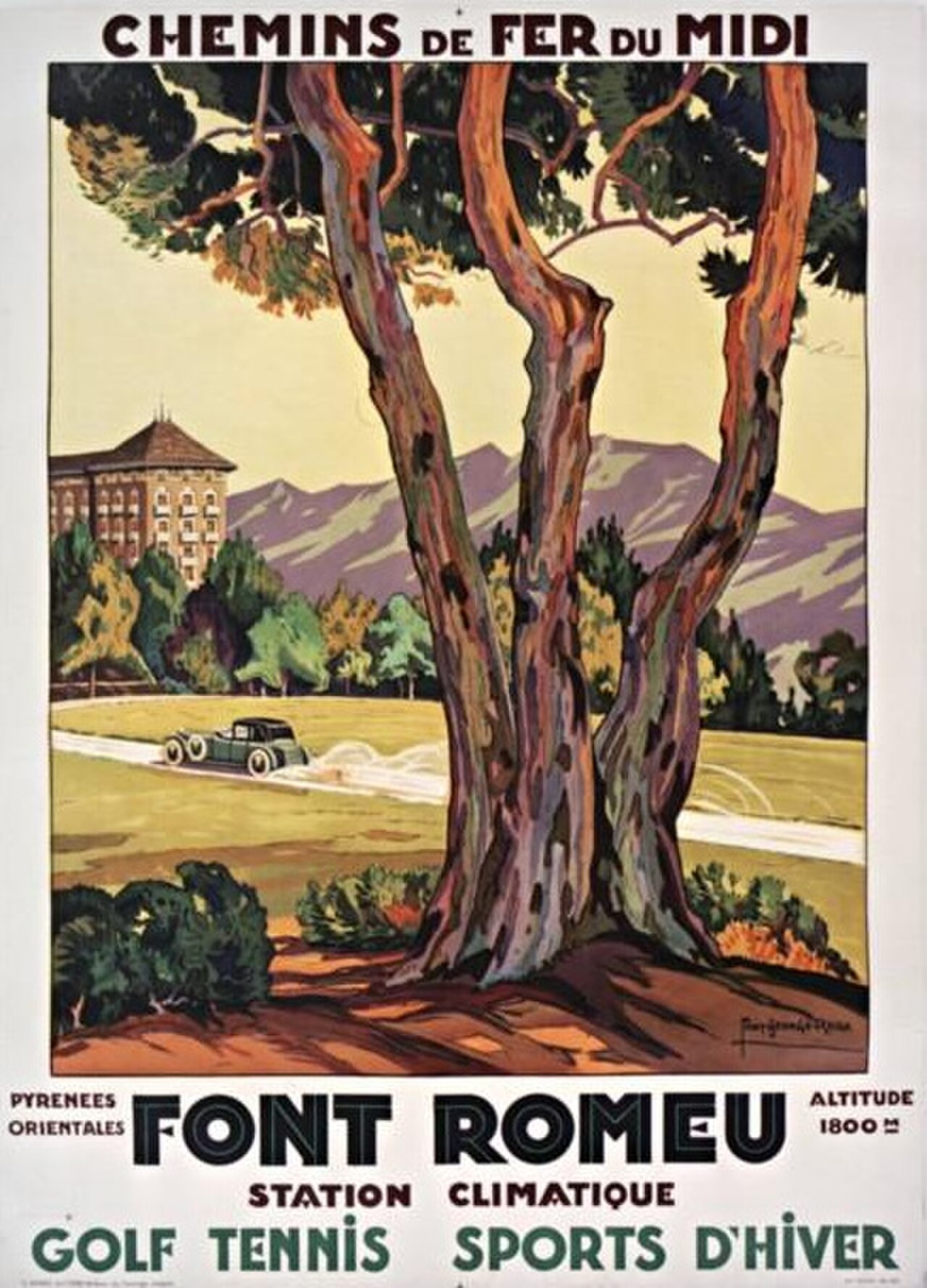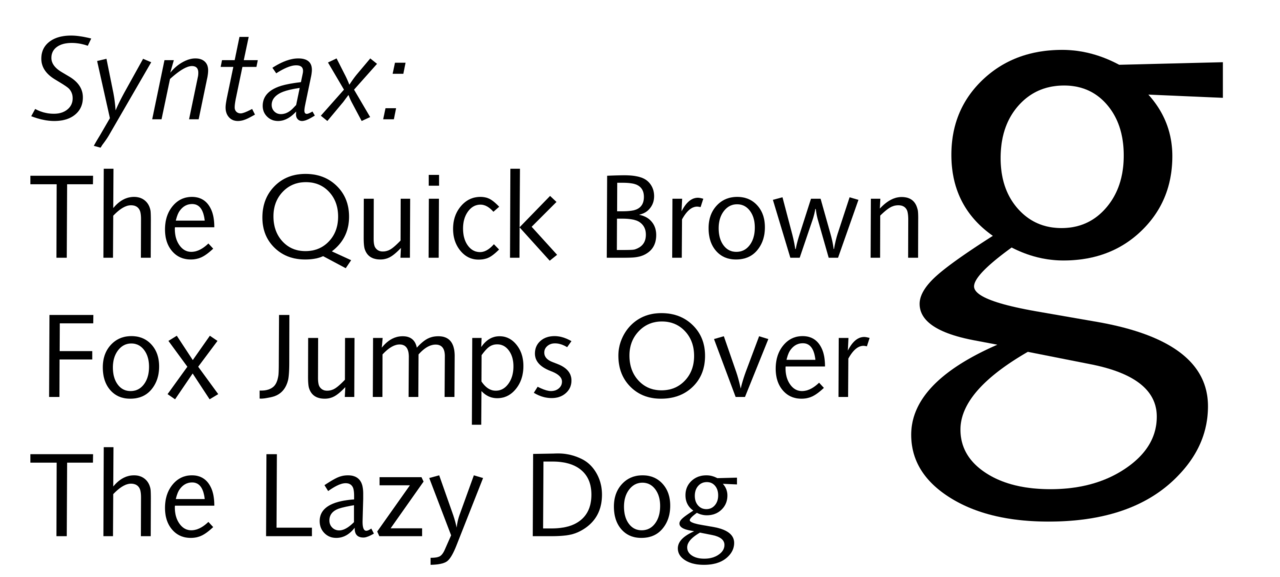
بدون تشعبات
| خط بدون تشعبات | |
| خط سيريف | |
| الخطوط المنحنية (ملونة باللون الأحمر) |
في الطباعة والكتابة ، الخط الخالي من التذييلات ( / ˈsæn ( z ) ˈsɛrɪf / ) أو القوطي أو ببساطة شكل الحرف الخالي من التذييلات هو الخط الذي لا يحتوي على ميزات ممتدة تسمى " التذييلات " في نهاية الضربات. [1] تميل الخطوط الخالية من التذييلات إلى أن يكون لها تباين أقل في عرض الضربات من الخطوط ذات التذييلات . غالبًا ما تُستخدم لنقل البساطة والحداثة أو الحد الأدنى . لأغراض تصنيف النوع، يتم تقسيم التصميمات الخالية من التذييلات عادةً إلى هذه المجموعات الرئيسية: § غريب، § غريب حديث، § هندسي، § إنساني، و§ آخر أو مختلط.
أصبحت الخطوط الخالية من التشعبات هي الأكثر انتشارًا لعرض النصوص على شاشات الكمبيوتر. على شاشات العرض الرقمية ذات الدقة المنخفضة، قد تختفي التفاصيل الدقيقة مثل التشعبات أو تظهر كبيرة جدًا. يأتي المصطلح من الكلمة الفرنسية sans ، والتي تعني "بدون" و"تشعبات" من أصل غير مؤكد، ربما من الكلمة الهولندية schreef والتي تعني "خط" أو ضربة قلم. [2] في الوسائط المطبوعة، تُستخدم بشكل أكثر شيوعًا لاستخدام العرض وأقل للنص الأساسي .
قبل أن يصبح مصطلح "sans-serif" معيارًا في الطباعة الإنجليزية، كان يتم استخدام عدد من المصطلحات الأخرى. أحد هذه المصطلحات لـ sans-serif كان "grotesque"، والذي يستخدم غالبًا في أوروبا، و" gothic "، والذي لا يزال يستخدم في الطباعة في شرق آسيا ويُرى أحيانًا في أسماء الخطوط مثل News Gothic أو Highway Gothic أو Franklin Gothic أو Trade Gothic .
تُستخدم الخطوط الخالية من التشعبات أحيانًا، وخاصة في المستندات القديمة، كأداة للتأكيد ، بسبب لون الكتابة الأسود عادةً .
تصنيف
لأغراض تصنيف النوع، يتم تقسيم التصميمات الخالية من التشعبات عادةً إلى ثلاث أو أربع مجموعات رئيسية، المجموعة الرابعة هي نتيجة تقسيم فئة الغروتسك إلى الغروتسك والغروتسك الجديد. [3] [4]
غريب الأطوار
تتميز هذه المجموعة بمعظم التصميمات الخالية من التشعبات المبكرة (من القرن التاسع عشر إلى أوائل القرن العشرين). وقد تأثرت هذه التصميمات بخطوط ديدون ذات التشعبات في تلك الفترة وتقاليد رسم اللافتات، وكانت غالبًا تصميمات قوية وجريئة مناسبة للعناوين والإعلانات. غالبًا ما لم تتميز الخطوط الخالية من التشعبات المبكرة بأحرف صغيرة أو مائلة ، حيث لم تكن هناك حاجة إليها لمثل هذه الاستخدامات. وقد تم إصدارها أحيانًا بالعرض، مع مجموعة من العروض من الممتد إلى العادي إلى المكثف، مع اختلاف كل نمط، مما يعني أنها قد تبدو غير منتظمة وغريبة للعين الحديثة. [5] [6]
تتميز الخطوط الغريبة بتنوع محدود في عرض الخط (غالبًا ما لا يكون محسوسًا في الأحرف الكبيرة). تكون نهايات المنحنيات أفقية عادةً، والعديد منها يحتوي على حرف "G" مدبب وحرف "R" مع ساق ملتفة. تميل الأحرف الكبيرة إلى أن تكون بعرض موحد نسبيًا. يكون ارتفاع الحرف الكبير وارتفاع الصاعد متماثلين بشكل عام لإنتاج تأثير أكثر انتظامًا في النصوص مثل العناوين التي تحتوي على العديد من الأحرف الكبيرة، وغالبًا ما تكون الأحرف الهابطة قصيرة للحصول على مسافة أضيق بين السطور. [7] غالبًا ما تتجنب استخدام الخط المائل الحقيقي لصالح تصميم مائل أو منحدر أكثر تحفظًا، على الرغم من تقديم بعض الخطوط المائلة الحقيقية الخالية من التشعبات على الأقل. [8] [9]
تشمل أمثلة الخطوط الغريبة الخطوط Akzidenz-Grotesk و Venus و News Gothic و Franklin Gothic و IBM Plex و Monotype Grotesque . تعد خطوط Akzidenz Grotesk Old Face وKnockout و Grotesque No. 9 وMonotype Grotesque أمثلة للخطوط الرقمية التي تحتفظ بمزيد من غرابة بعض الخطوط الخالية من التشعبات المبكرة. [10] [11] [12] [13]
وفقًا لمونوتيب، فإن مصطلح "grotesque" نشأ من الكلمة الإيطالية : grottesco ، والتي تعني "الانتماء إلى الكهف" نظرًا لمظهرها الهندسي البسيط. [14] نشأ المصطلح بسبب المقارنات المعاكسة التي أجريت مع الخطوط الأكثر زخرفة Modern Serif وRoman والتي كانت القاعدة في ذلك الوقت. [15]
نيوغروتسك
ظهرت التصميمات الجروتسكية الجديدة في منتصف القرن العشرين كتطور للأنواع الجروتسكية. وهي بسيطة نسبيًا في المظهر مع اختلاف محدود في عرض الخطوط. وعلى غرار الخطوط الجروتسكية، غالبًا ما تتميز الخطوط الجروتسكية الجديدة بأحرف كبيرة بعرض موحد وتصميم "مطوي" إلى حد ما، حيث تكون الخطوط (على سبيل المثال حرف "c") منحنية بالكامل لتنتهي على خط أفقي أو رأسي مثالي. يعد خط Helvetica مثالاً على ذلك. على عكس التصميمات الجروتسكية السابقة، تم إصدار العديد منها في مجموعات كبيرة منذ وقت الإصدار.
بدأ ظهور الخط الجروتسك الجديد في الخمسينيات من القرن العشرين مع ظهور النمط الطباعي الدولي ، أو النمط السويسري. نظر أعضاؤه إلى الخطوط الواضحة لـ Akzidenz-Grotesk (1898) كمصدر إلهام للتصميمات ذات المظهر المحايد واللون المتساوي على الصفحة. في عام 1957، كان لإصدار Helvetica و Univers و Folio ، أول الخطوط المصنفة على أنها جروتسك جديدة، تأثير قوي على المستوى الدولي: أصبح Helvetica هو الخط الأكثر استخدامًا في العقود التالية. [16] [ب] [ بحاجة لمصدر أفضل ]
هندسي
تعتمد الخطوط الهندسية الخالية من التشعبات على أشكال هندسية، مثل الدوائر والمربعات شبه الكاملة. [18] ومن السمات المشتركة الحرف الكبير "O" الدائري تقريبًا، ورؤوس الحرف الكبير "N" الحادة والمدببة، والحرف الصغير "a" "المكون من طابق واحد". غالبًا ما يكون الحرف "M" متباعدًا والحروف الكبيرة بعرض متفاوت، وفقًا للنموذج الكلاسيكي .
نشأت الخطوط الهندسية السانس في ألمانيا في عشرينيات القرن العشرين. [19] تم بذل محاولتين مبكرتين في تصميم الخطوط الهندسية من قبل هربرت باير وجاكوب إربار ، اللذان عملا على Universal Typeface (لم يتم إصداره في ذلك الوقت ولكن تم إحياؤه رقميًا باسم Architype Bayer ) و Erbar ( حوالي عام 1925 ). [20] في عام 1927، تم إصدار Futura ، بواسطة بول رينر ، وحظي بإشادة كبيرة وشعبية. [21]
كانت الخطوط الهندسية الخالية من التشعبات شائعة في عشرينيات وثلاثينيات القرن العشرين بسبب تصميمها النظيف والحديث، وقد تم تطوير العديد من التصميمات الهندسية الجديدة والإحياء منذ ذلك الحين. [ج] تشمل الأنواع الهندسية البارزة في تلك الفترة Kabel و Semplicità و Bernhard Gothic و Nobel و Metro ؛ تشمل التصميمات الأحدث في هذا النمط ITC Avant Garde و Brandon Grotesque و Gotham و Avenir و Product Sans و HarmonyOS Sans و Century Gothic . كانت العديد من الأبجديات الهندسية الخالية من التشعبات في تلك الفترة، مثل تلك التي ألفتها مدرسة باوهاوس للفنون (1919-1933) وفناني الملصقات الحداثيين، مكتوبة يدويًا ولم يتم قطعها في حروف معدنية في ذلك الوقت. [23]